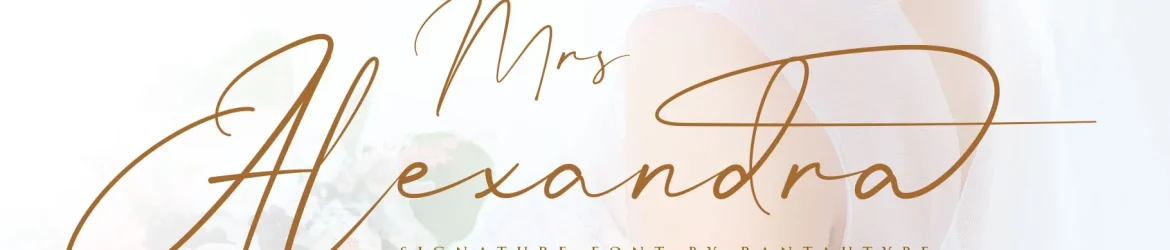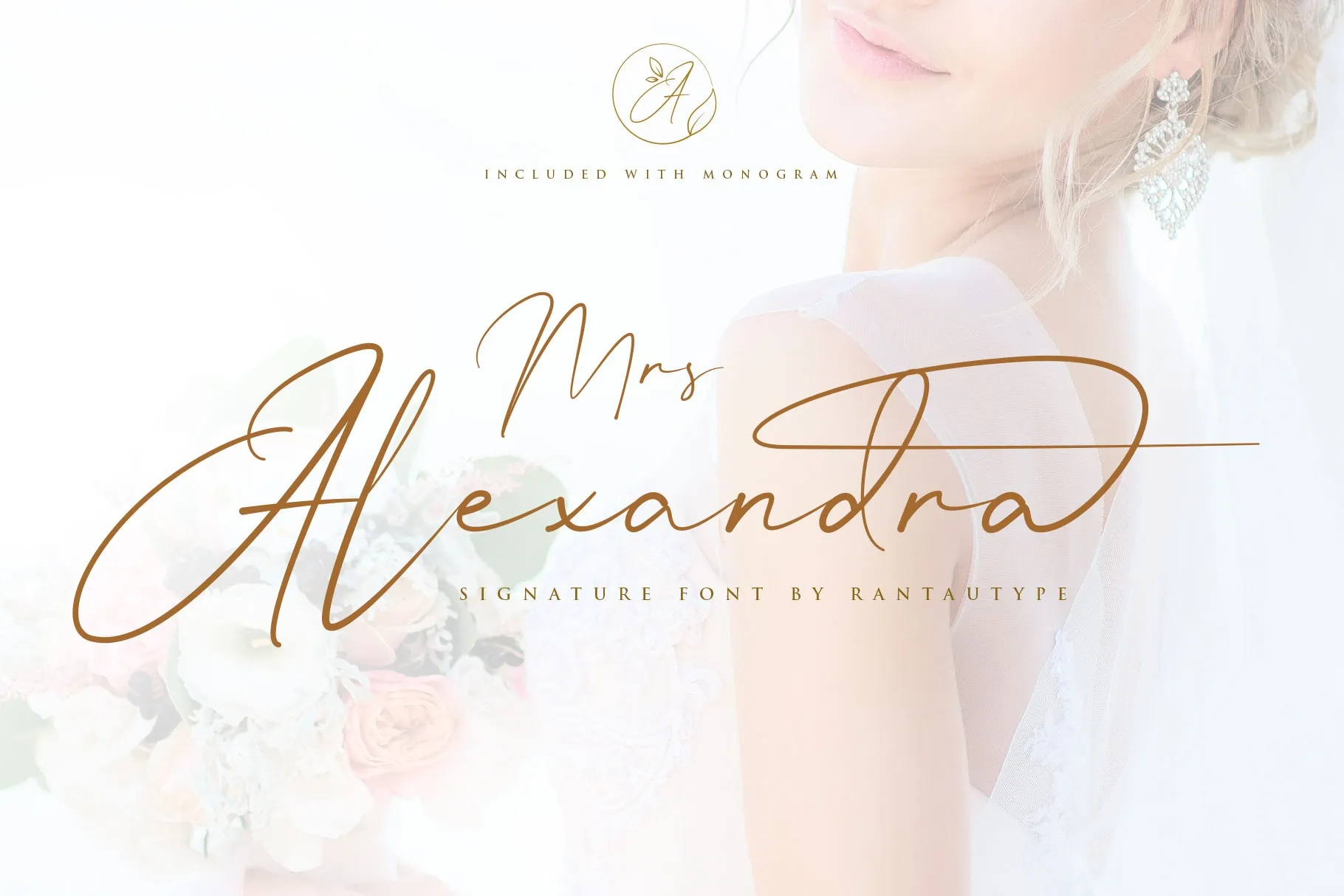
Mrs Alexandra Script Font – Fonte Grátis
Mrs Alexandra Script Font
A Mrs Alexandra Script Font é uma escolha perfeita para quem busca dar um toque único às suas obras de arte digitais. Inspirada num estilo elegante e moderno, essa fonte script oferece a oportunidade de personalizar seu próximo projeto com uma aparência sofisticada e arrojada. Ideal para o design de marca, como assinaturas ou logos assinados, ela se adapta perfeitamente a trabalhos variados como cartões de visita, capas de álbuns, códigos de produto, logotipos e até mesmo criações publicitárias. As letras fluidas e arredondadas da Mrs Alexandra são ideais para criar um design que chama atenção, seja em uma camiseta personalizada ou numa capa de livro. Com a Clafita Miller por trás desta fonte sofisticada, seu trabalho pode ser elevado a um novo nível de elegância e originalidade. Descubra o encanto da Mrs Alexandra Script Font e transforme sua arte digital em algo único e memorável.